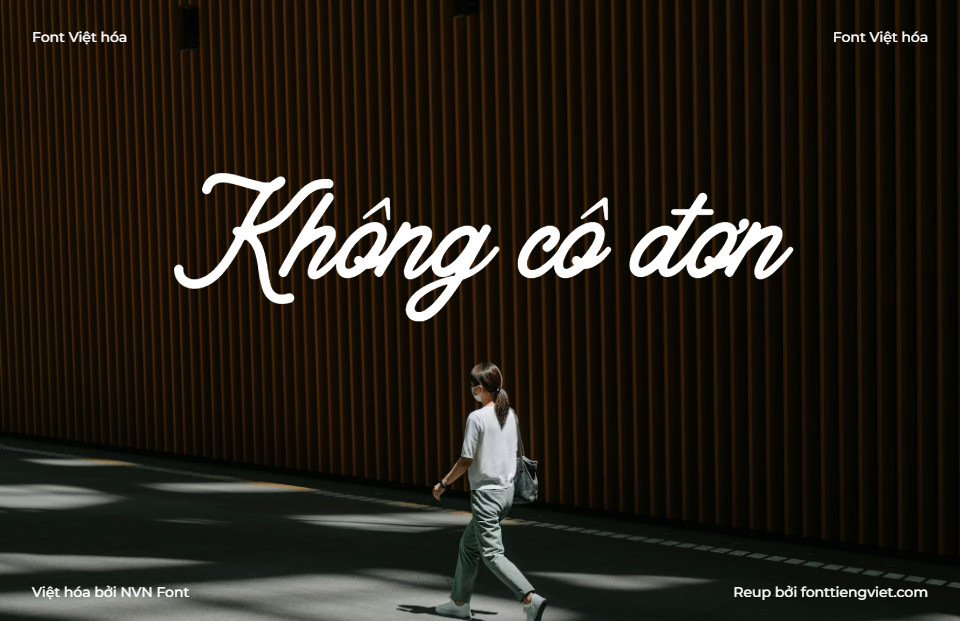
Font Việt hoá NVN Northland Script – Sự Lựa Chọn Hoàn Hảo Cho Thiết Kế Sáng Tạo
Trong thế giới thiết kế đồ họa hiện nay, việc lựa chọn một bộ Font Miễn Phí chất lượng luôn là ưu tiên hàng đầu của các bạn trẻ và những người làm sáng tạo. Font Việt hoá NVN Northland Script nổi lên như một hiện tượng nhờ vẻ đẹp thanh tao, mềm mại và mang đậm hơi hướng nghệ thuật viết tay thủ công. Đây không chỉ đơn thuần là một kiểu chữ, mà còn là công cụ đắc lực giúp truyền tải cảm xúc và cá tính riêng biệt vào từng ấn phẩm thiết kế. Đối với cộng đồng thiết kế tại Việt Nam, việc sở hữu những bộ font đã được Việt hóa chỉn chu giúp tiết kiệm thời gian đáng kể trong quá trình xử lý văn bản, đảm bảo không bị lỗi dấu tiếng Việt khi sử dụng trên các phần mềm phổ biến.
Khám phá vẻ đẹp độc đáo của Font Việt hoá NVN Northland Script
Bộ font này được lấy cảm hứng từ những nét chữ script truyền thống nhưng đã được tinh chỉnh để trở nên hiện đại và thanh thoát hơn. Đặc điểm nhận dạng của Font Việt hoá NVN Northland Script chính là các đường nét nối liền mạch, tạo cảm giác uyển chuyển như những dòng nước chảy. Các ký tự được thiết kế với độ tương phản nhẹ nhàng giữa nét thanh và nét đậm, giúp tổng thể văn bản trở nên hài hòa và dễ nhìn. Đặc biệt, bộ font này cực kỳ phù hợp cho những dự án yêu cầu sự sang trọng nhưng vẫn giữ được nét gần gũi, mộc mạc.
Tính ứng dụng linh hoạt trong đời sống và học tập
Với các bạn học sinh và sinh viên, Font Việt hoá NVN Northland Script là người bạn đồng hành lý tưởng để trang trí bìa tiểu luận, làm thiệp chúc mừng thầy cô hay thiết kế những bảng kế hoạch học tập cá nhân sinh động. Trong lĩnh vực thương mại, font chữ này thường được các nhà thiết kế ưu ái sử dụng cho logo các thương hiệu handmade, thực đơn nhà hàng, thiệp cưới hoặc các ấn phẩm truyền thông trên mạng xã hội. Khả năng tương thích tốt giúp người dùng dễ dàng ứng dụng trên cả nền tảng in ấn lẫn kỹ thuật số mà vẫn giữ được độ sắc nét và chuyên nghiệp tuyệt đối.
Ưu điểm vượt trội khi sử dụng Font Việt hoá NVN Northland Script
Lý do khiến Font Việt hoá NVN Northland Script được yêu thích chính là bảng mã tiếng Việt đầy đủ và chuẩn xác. Bạn sẽ không còn gặp phải tình trạng các ký tự có dấu bị nhảy font hoặc biến dạng gây mất thẩm mỹ. Ngoài ra, bộ font này còn cung cấp nhiều ký tự thay thế (alternates) và các nét uốn lượn (swashes) mở rộng, cho phép người dùng tự do sáng tạo và biến hóa kiểu chữ theo ý thích cá nhân. Điều này đặc biệt quan trọng trong việc tạo ra những điểm nhấn độc đáo cho các tiêu đề hoặc các đoạn trích dẫn quan trọng trong bài thiết kế của bạn.
Lưu ý khi sử dụng font chữ trong thiết kế chuyên nghiệp
Mặc dù mang vẻ đẹp nghệ thuật cao, người dùng cần lưu ý kết hợp Font Việt hoá NVN Northland Script với các font chữ không chân (sans-serif) hoặc có chân (serif) đơn giản để đảm bảo tính phân cấp thông tin rõ ràng. Không nên sử dụng quá nhiều chữ script trong một đoạn văn dài vì có thể gây mỏi mắt cho người đọc. Hãy dùng nó như một điểm nhấn tinh tế để làm nổi bật thông điệp chính mà bạn muốn gửi gắm. Việc nắm vững các nguyên tắc phối hợp font sẽ giúp tác phẩm của bạn đạt được sự cân bằng hoàn hảo giữa tính thẩm mỹ và công năng sử dụng.